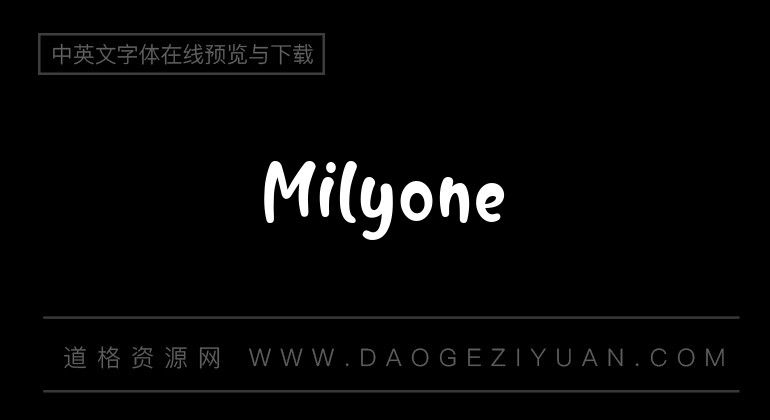
Milyone
Milyone 字体是一种由欧洲设计师创作的英文字体,它具有独特的外观,拥有非常优秀的可读性。Milyone 字体的字形设计简洁大方,具有非常醒目的视觉效果,可以用于各种不同的文字排版,比如广告、标语、标题等。Milyone 字体的字体大小可以自由调整,可以让文字更加清晰、易读,让文字更加生动有趣。
Milyone是一款非常不错的手写艺术字体,具有很好的视觉感,适合于文化类的宣传设计、商业类品牌的广告和产品包装设计以及个性化文字排版等较多场景。